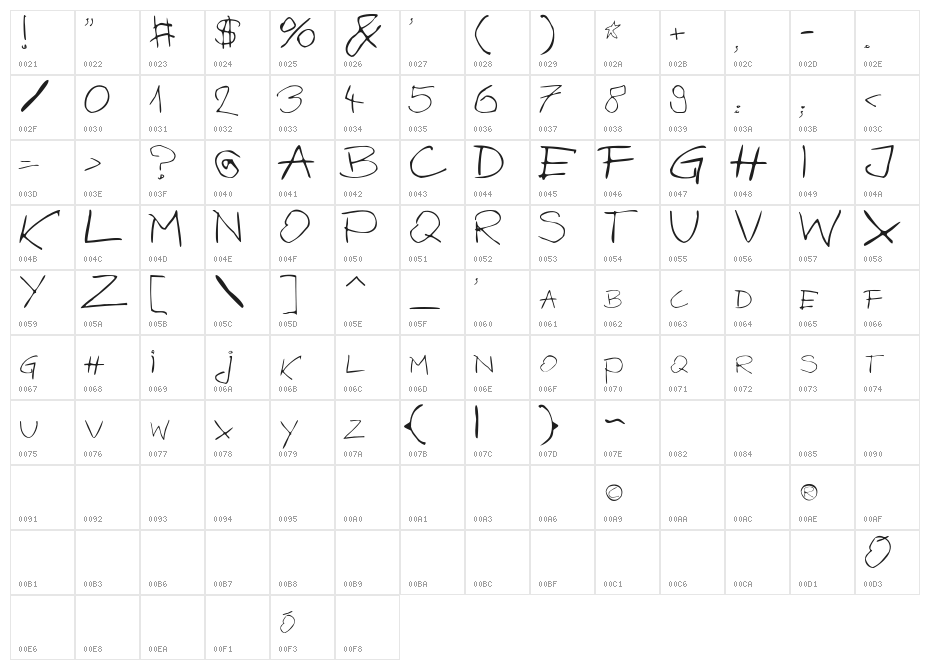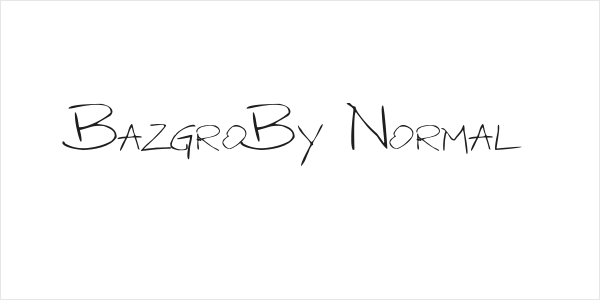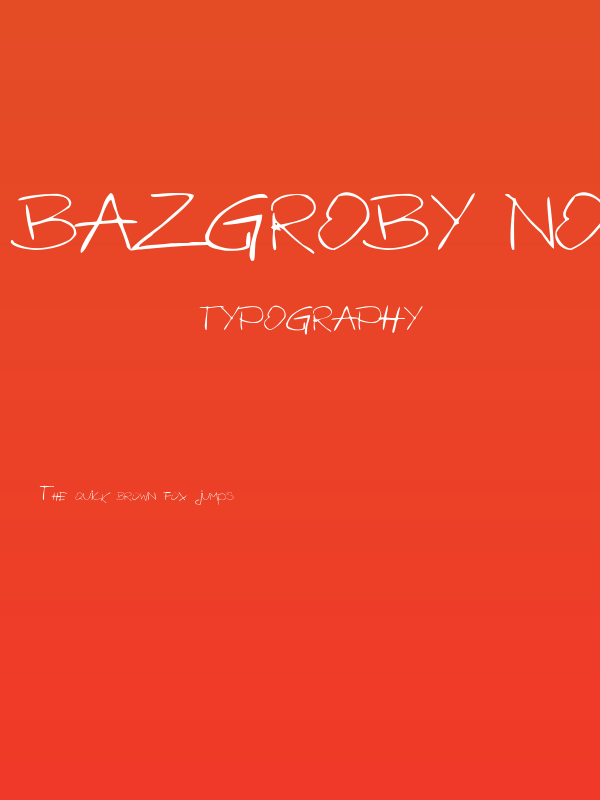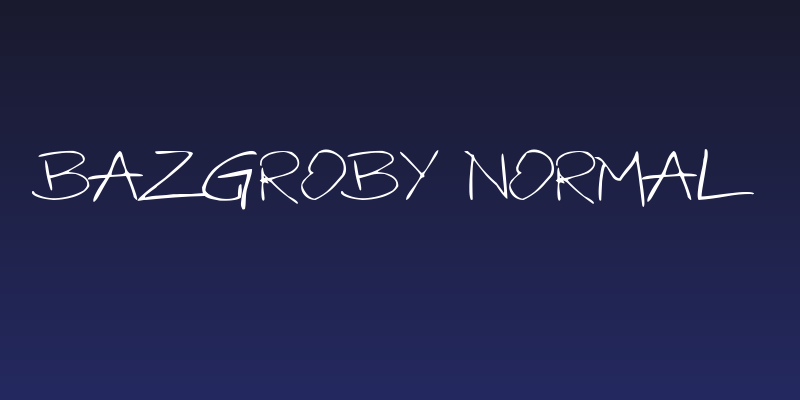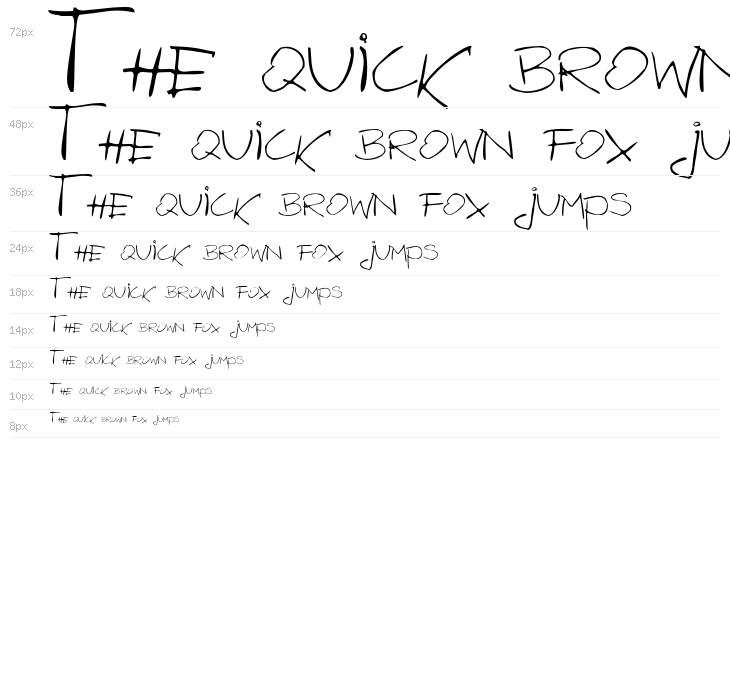
BazgroBy Normal Font
| Caz de utilizare | Logos, Invitations, Greeting Cards |
| Proiecte propuse | Ideal for greeting cards, children's books, casual invitations, and playful branding. |